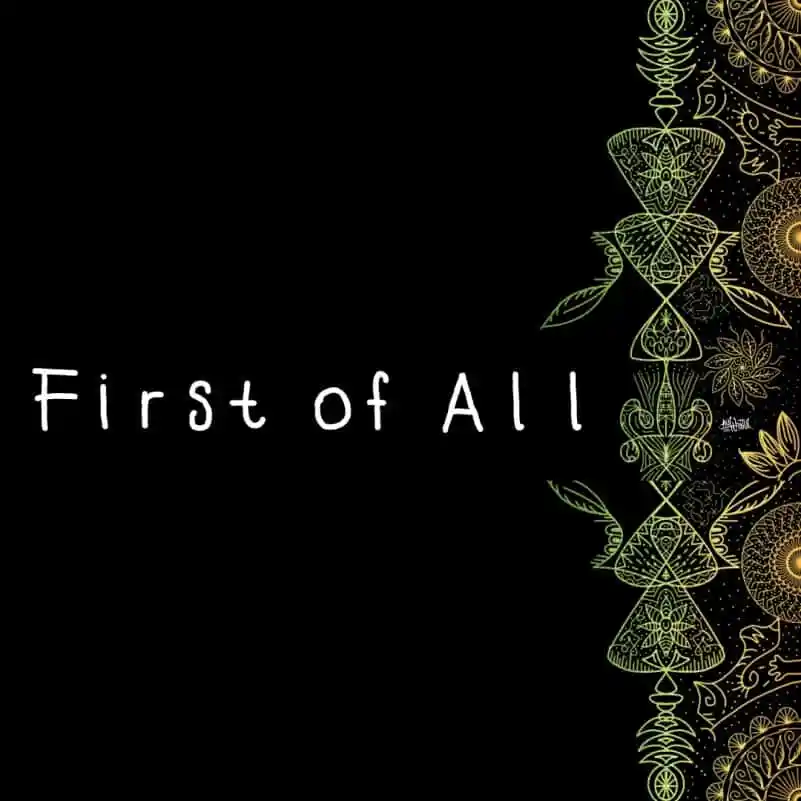
First of All Handwritten Font – Download Grátis
A First of All Handwritten Font é uma tipografia feita à mão inspirada na minha escrita para diários em fichas. Esta fonte ideal para uso no planner ou em aplicativos de fichas digitais, bem como labels, identificação de ícones, cartões-posters e muito mais. Suave e pessoal, ela traz uma dose de personalidade a qualquer projeto digital que você possa imaginar. Este tipo foi criado pela mão de um artista grafiti com uma paixão por criação visual, projetos de arte digital e estudos de letras escritas à mão. Seja para um logotipo elegante ou um post-it no seu computador, a First of All Handwritten Font está aqui pra ajudar você a dar vida à sua ideia.